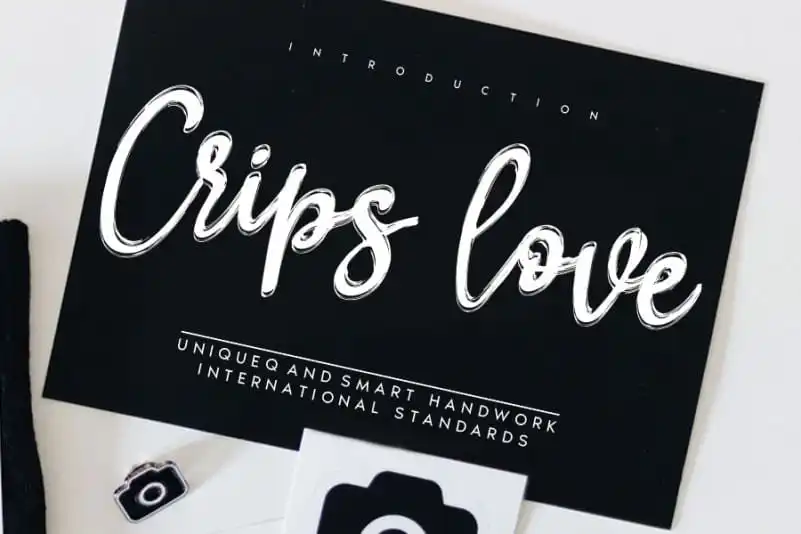
Crips love Script Font – Download Grátis
A Crips love Script Font é uma fonte escrita à mão que transmite a amizade instantânea do primeiro encontro. Desenhada com um estilo casual e cômico, esta fonte vem com suaves acabamentos de letras e ligaduras perfeitas para personalizar diversos projetos de design, seja branding ou logotipos, cabeçalhos ou designs de aniversários, convites ou assinaturas. É uma escolha ideal para aprimorar qualquer projeto que você está criando, proporcionando um toque único e pessoal. Essa fonte é tão versátil quanto ela é encantadora, dando vida à sua criação com seu estilo inconfundível.